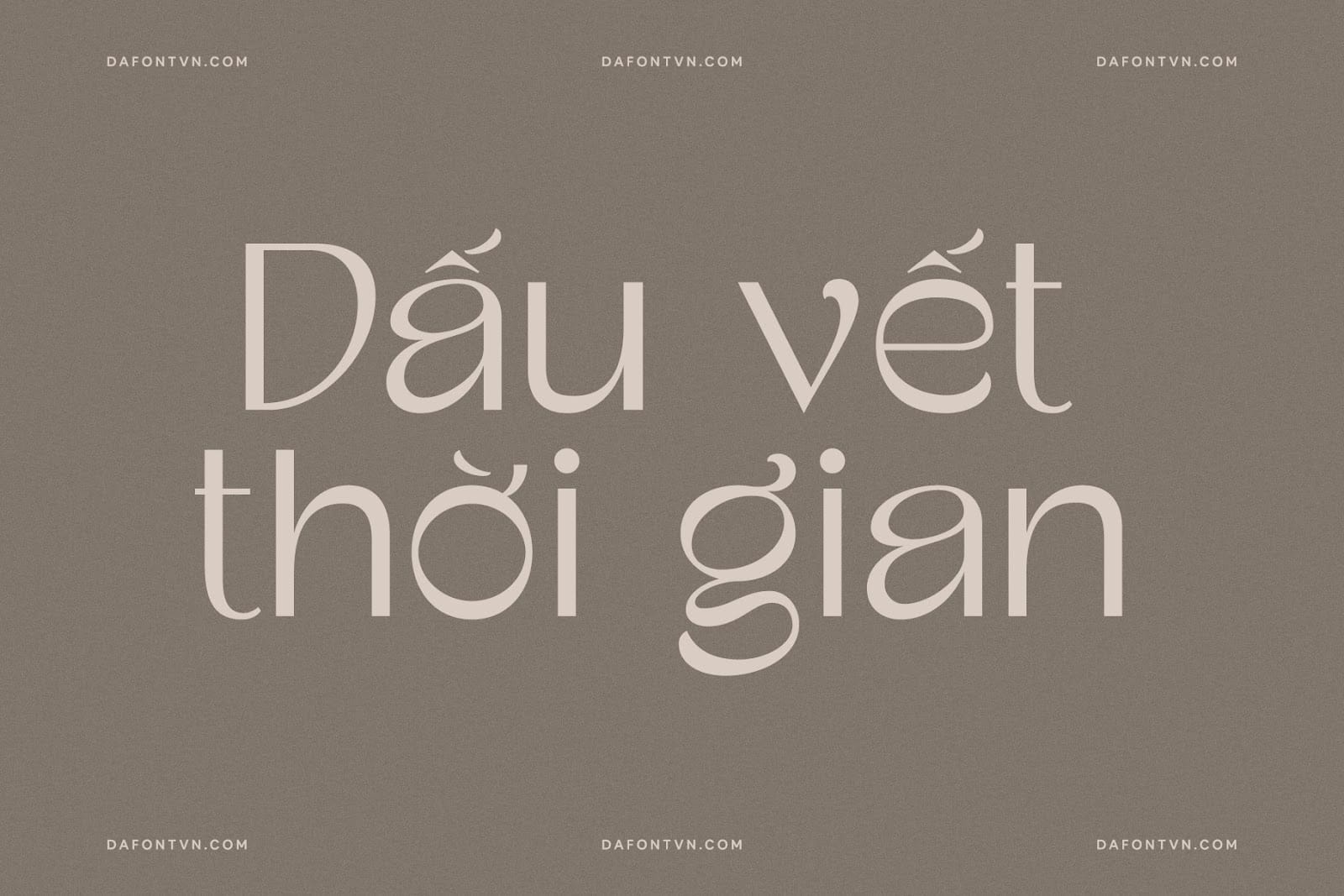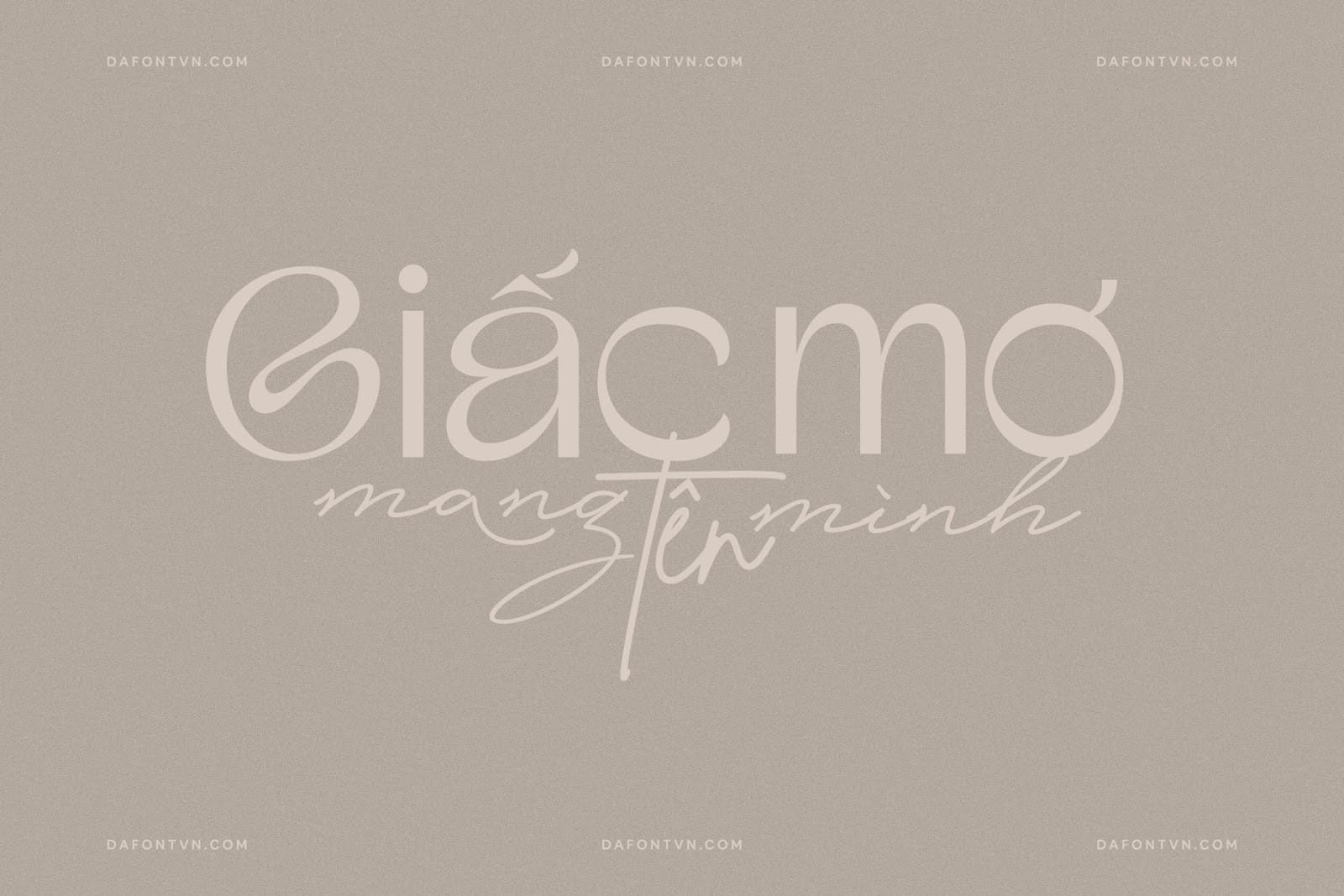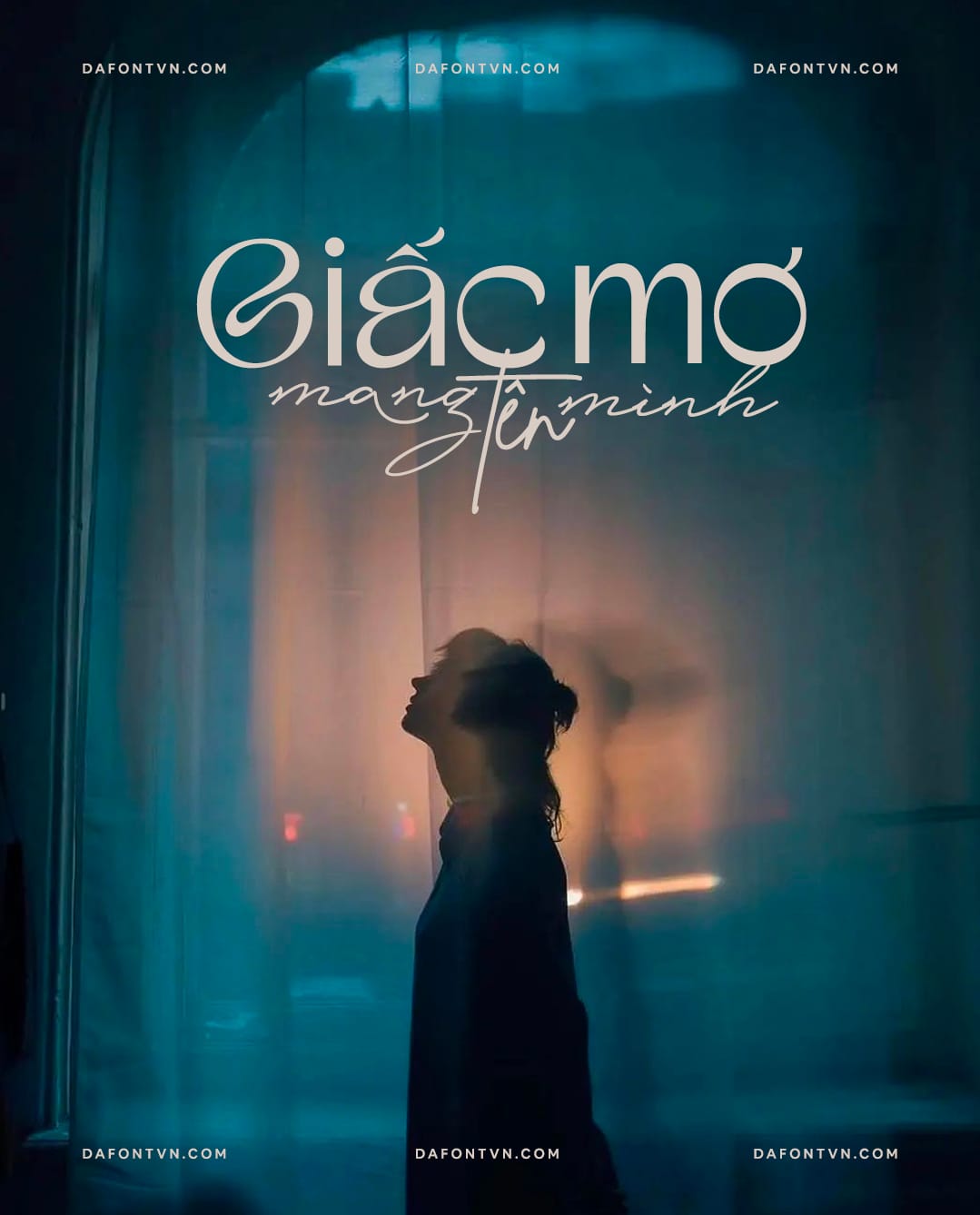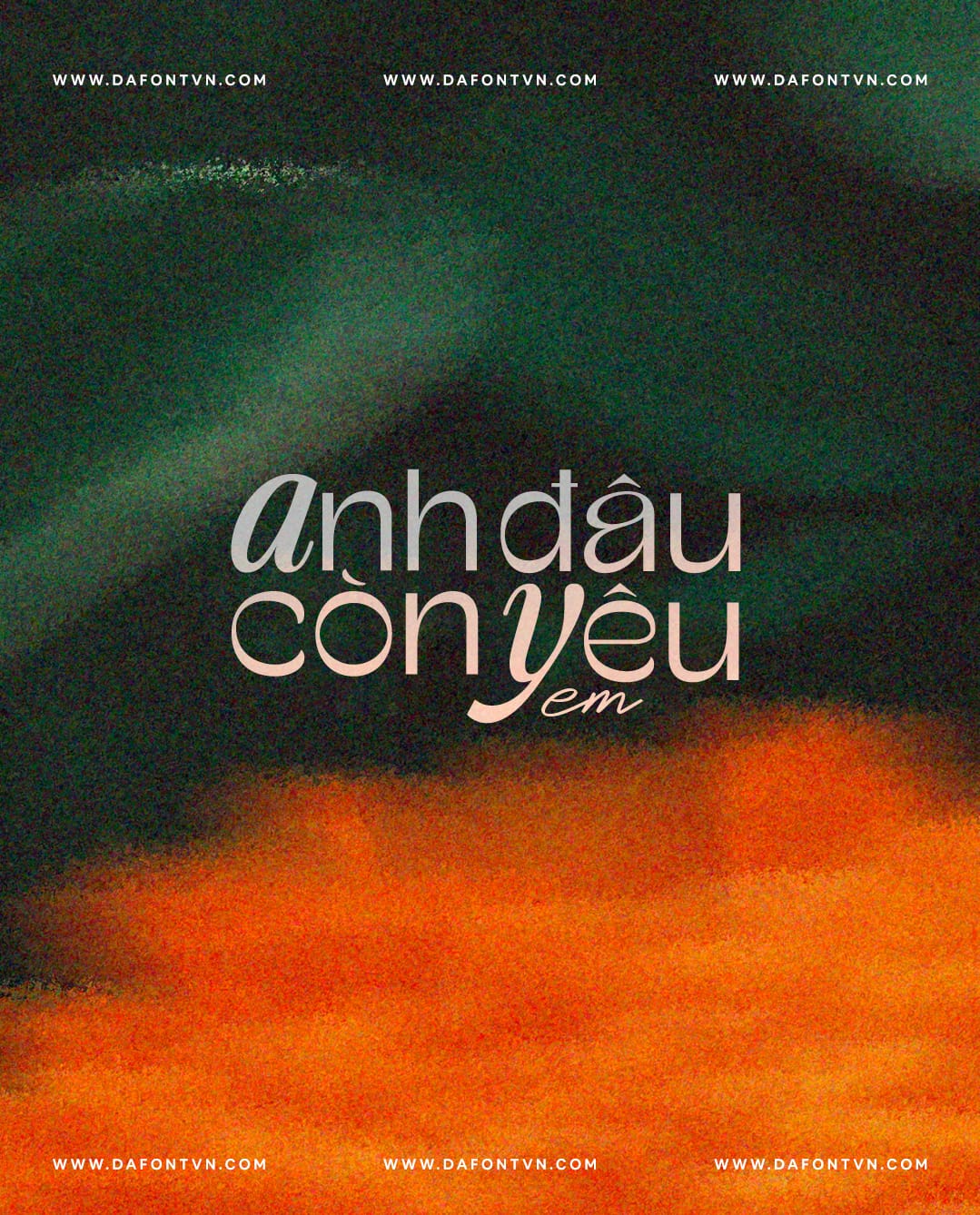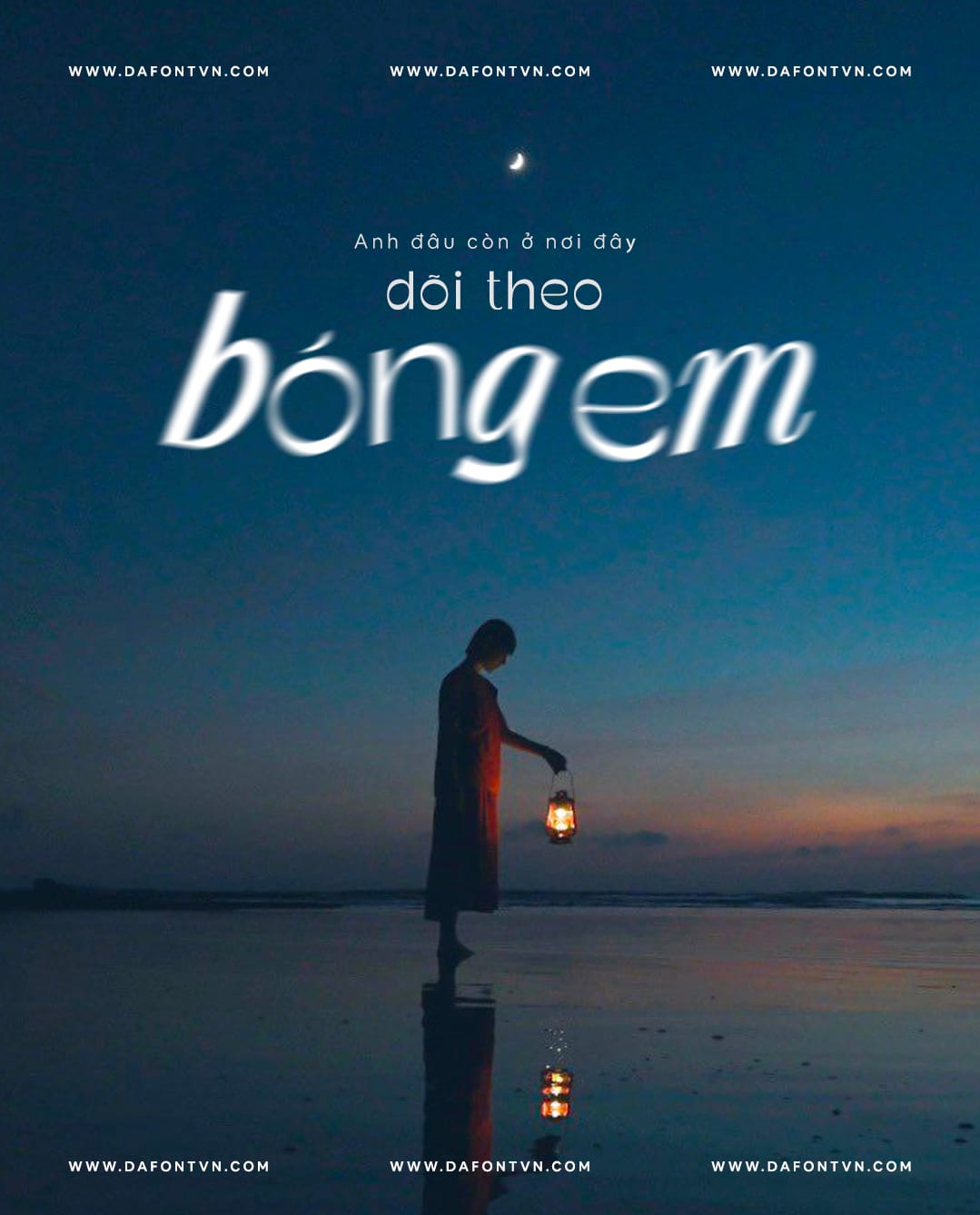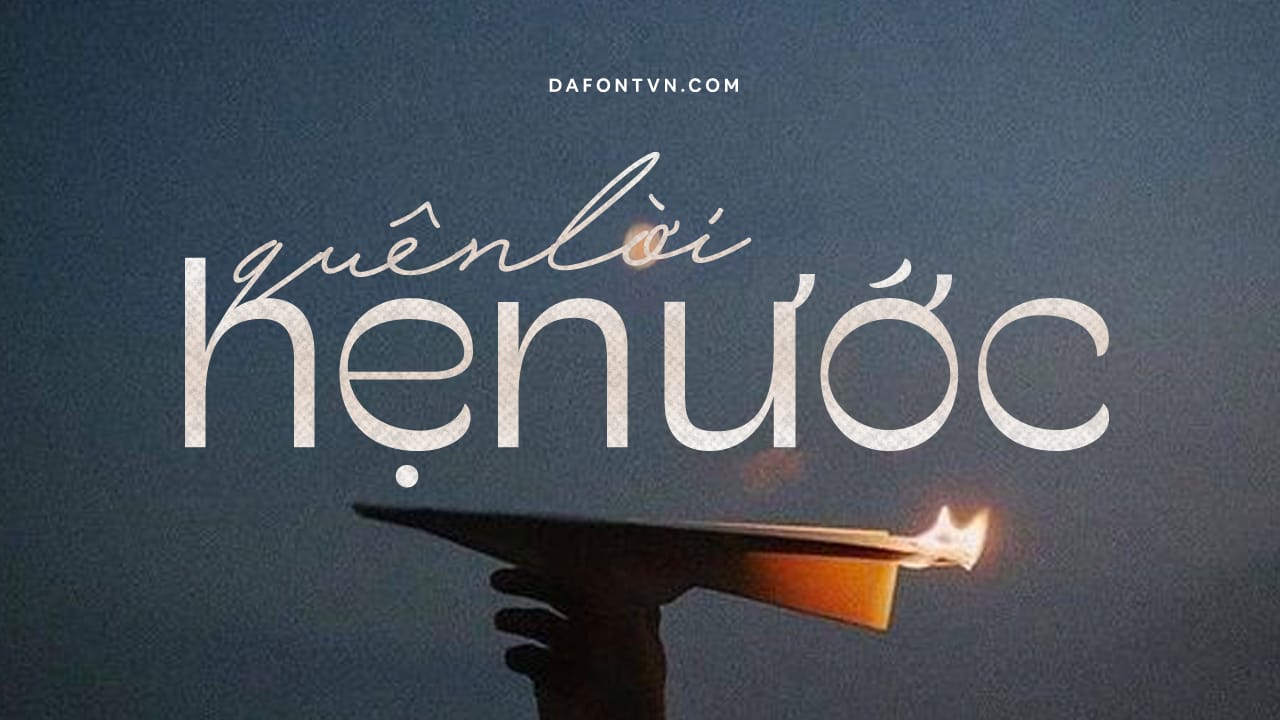
TAN – SPRING là kiểu chữ lấy cảm hứng từ retro nhưng vẫn mang trong mình vẻ đẹp của sự hiện đại. Nó được thiết kế với hình dạng gọn gàng với một số nét chữ mềm mại ấn tượng.
Phông chữ này được thiết kế hoàn hảo để sử dụng cho logo, tiêu đề, tạp chí, thiệp mời, nhãn hiệu, bao bì, thời trang hoặc bất kỳ thiết kế nào khác.Font TAN – SPRING việt hóa đầy đủ. Ngoài ra, vì các dấu của font gốc khá nhỏ vì vậy mình đã sửa lại các dấu và ký tự cho to, rõ ràng hơn để hiển thị tốt nhất ở các kích thước khác nhau.